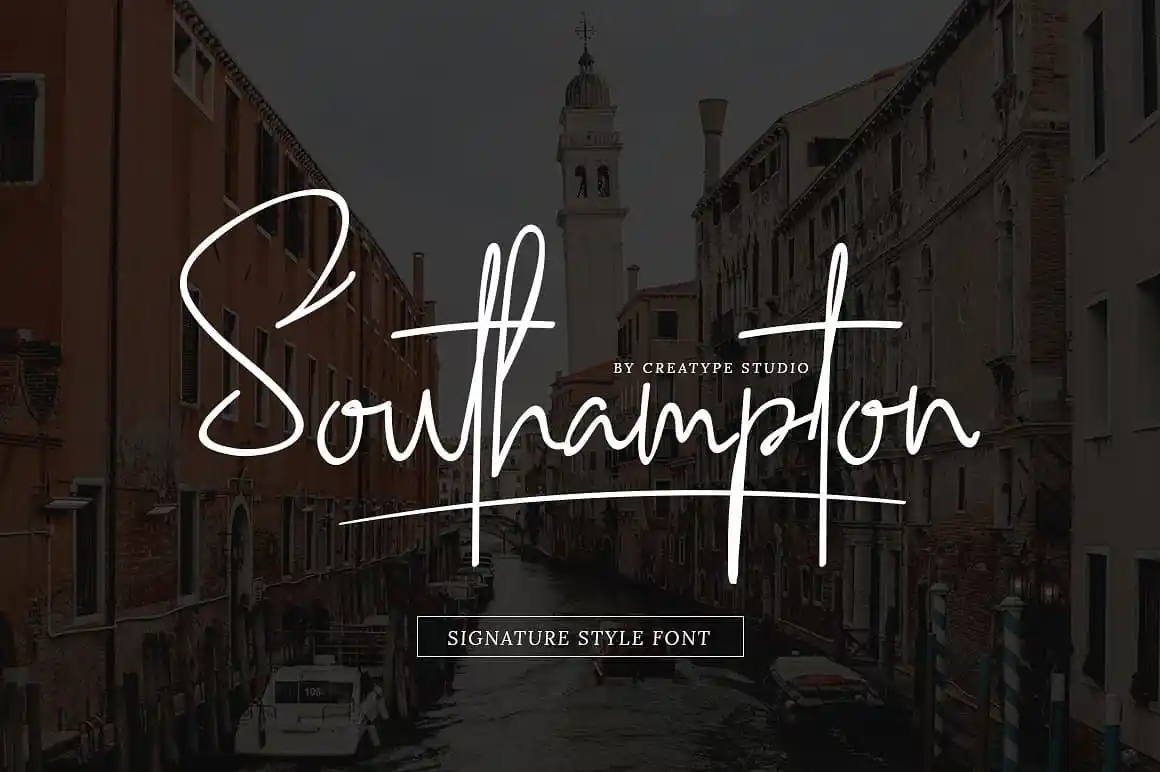
Southampton Signature Style Font
Olá amigos, introduzimos a Southampton – uma elegante e autêntica caligrafia com estilo único! Desenhada pelo Creatype Studio Co., esta fonte script oferece um toque pessoal para seus projetos de arte mais recentes. Com um ar elegantemente clássico e moderno, a Southampton traz beleza tipográfica perfeita para uma variedade de projemas, como logomarcas e identidade corporativa, convites, embalagens, designs de casamentos, posts nas redes sociais, anúncios, embalagens de produtos, rótulos, fotografia e até mesmo marcos especiais. A Southampton é perfeita para quem busca adicionar um toque pessoal aos seus projetos. Essa fonte script oferece uma maneira única de dar vida a suas idéias artísticas, seja em papel ou digital. Através da Southampton, você pode criar logomarcas e identidades corporativas impressionantes; tornar seus convites e embalagens mais elegantes; e até mesmo adicionar um toque autêntico aos seus posts nas redes sociais. Experimente a Southampton e descubra como ela transforma seu trabalho em arte única, com uma aparência moderna e classica ao mesmo tempo.